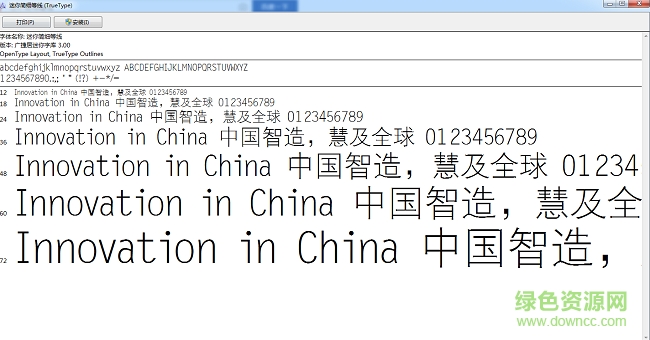
jxidengxian是什么?jxidengxian文字是一款細(xì)等線字體,筆畫清晰樸素,比較機(jī)械,等線字體也屬于無襯線字體,這種字體能夠彰顯你的個(gè)性,讓你所想表達(dá)的內(nèi)容也更加亮眼,歡迎需要的朋友來綠色資源網(wǎng)下載!
無襯線字體筆劃粗細(xì)均勻,比較簡(jiǎn)潔美觀,適用于單詞短句,適用于短句美感提升!